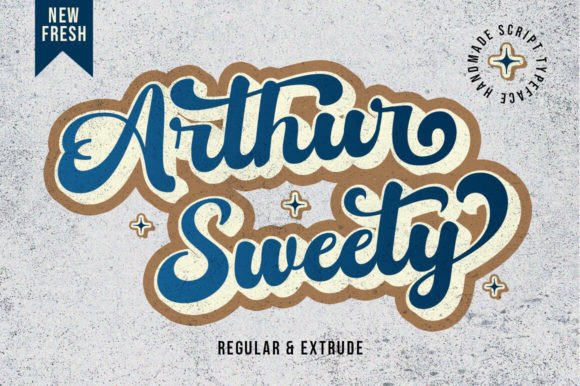
Arthur Sweety
إذا كنت تبحث عن أصول عالية الجودة مثل Arthur Sweety، فإن هذه الحزمة المميزة هي خيار رائع لمشاريعك الإبداعية.
سواء كنت تقوم بإنشاء منتجات الطباعة عند الطلب أو دعوات الزفاف أو رسومات وسائل التواصل الاجتماعي، فإن Arthur Sweety هو الخيار المثالي.